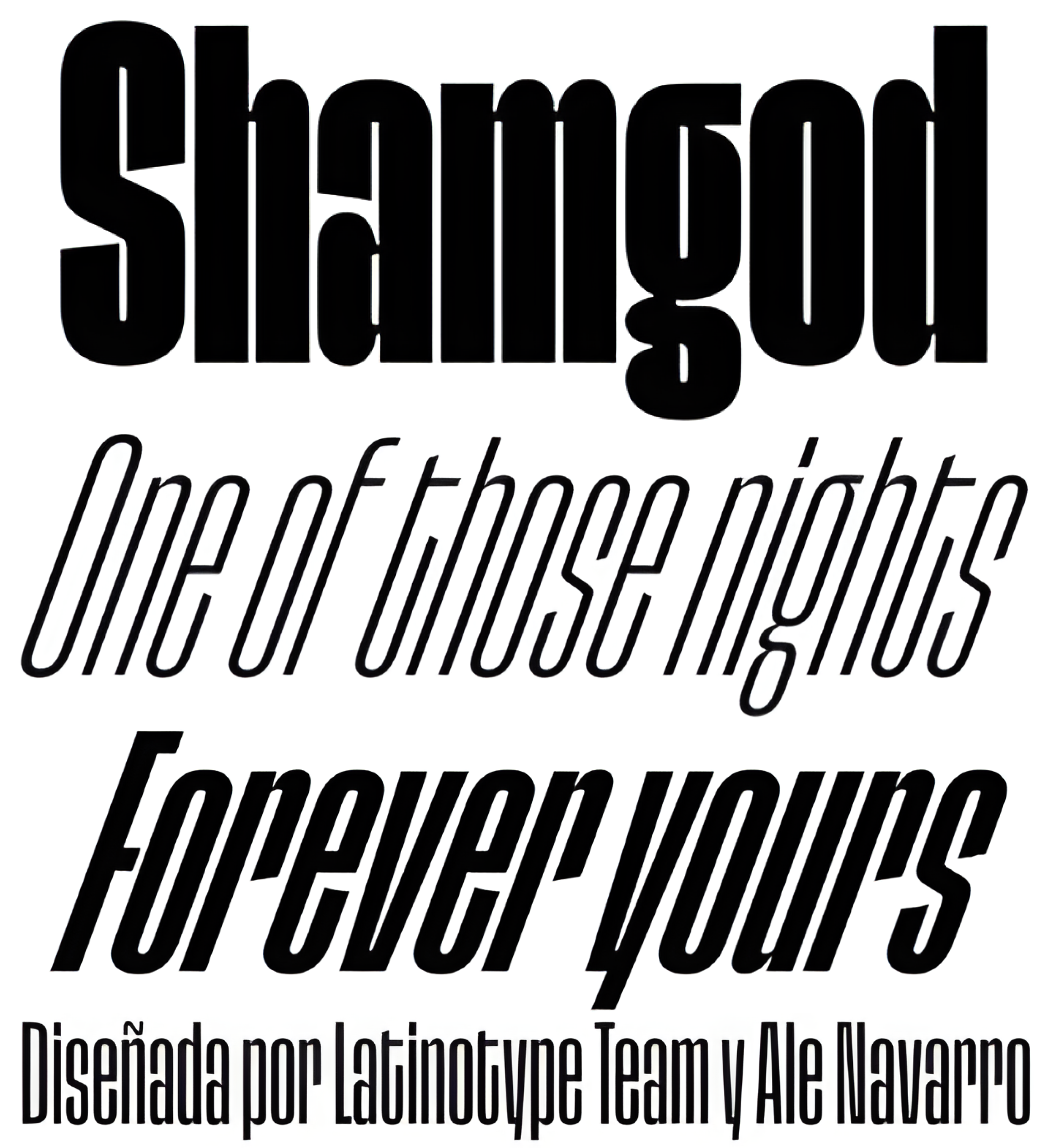
| Créditos | Ale Navarro, Latinotype Team |
| Descripción | Shamgod es un tipo de letra audaz y ultracondensado diseñado para destilar velocidad y energía. Su estilo grotesco, sus afilados cortes diagonales y su forma compacta captan la cruda intensidad de los deportes y la cultura urbana de los años 90 y 2000. Con su carácter expresivo, es perfecto para titulares llamativos, logotipos y marcas deportivas. Ideal para ropa urbana, diseño digital y marcas modernas, aporta una presencia fuerte y dinámica a cualquier proyecto. Tanto si se utiliza en carteles, identidades de marca o diseños editoriales, su impactante efecto visual lo convierte en una elección poderosa para quienes buscan una estética atrevida y contemporánea. Con sede en Concepción y Santiago de Chile, los fundadores de Latinotype afirman: «Nuestro objetivo es diseñar nuevos tipos de letra remezclando diversas influencias relacionadas con nuestra identidad sudamericana con productos de alta calidad para la industria del diseño contemporáneo». Y el dúo ha estado haciendo precisamente eso desde la creación de su fundición en 2007. Luciano Vergara y Daniel Hernández, una de las fundiciones de mayor éxito en MyFonts en los últimos años, han reunido una colección de tipos de letra en rápido crecimiento en una amplia gama de géneros. El nombre del grupo, «Latinotype», que se especializa en tipos de letra de gran colorido, subraya el fuerte vínculo que sienten con su identidad cultural. |
| Familia(s) | Shamgod |
| Estudio | Latinotype |